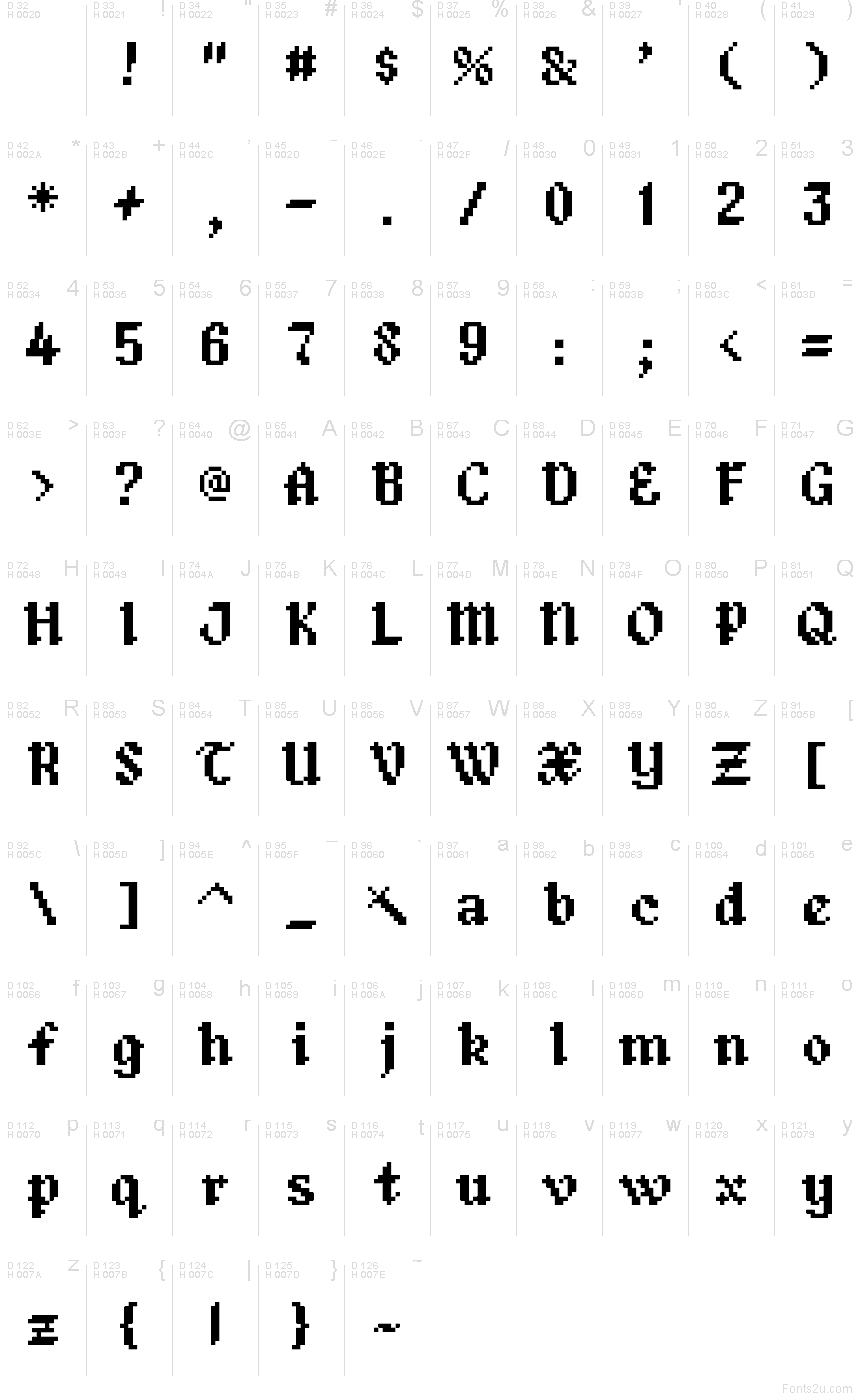
The Lowly Scribe od MagicBear je bezplatné pixelové písmo typu display, sestavené z výrazných čtvercových modulů. Jeho písmena kombinují vysoké blokové tahy s prudkými zářezy a odstupňovanými okraji. Nerovnoměrné vnitřní mezery dodávají písmu surový, ručně sestavený vzhled navzdory přísné mřížce.
Jeho vzhled připomínající staré herní obrazovky se hodí k názvům fantasy her a retro digitální grafice. Hranaté tvary se hodí také na hudební plakáty a merchandise s undergroundovým nebo DIY zaměřením. V herním rozhraní se písmena mohou stát součástí nápisu v dungeonu nebo vyřezávaného znaku na obrazovce namísto běžného textu.
The Lowly Scribe was built with FontStruct Designer description: <p>A mish-mash of various fantasy and medieval influences.</p><p>(Still a work in progress.)</p> Quill and Antler Expanded, which is based on Quill and Antler, which is based on Quill and Antler (outdated), which is based on Airmail Fantasy, which is based on Airmail